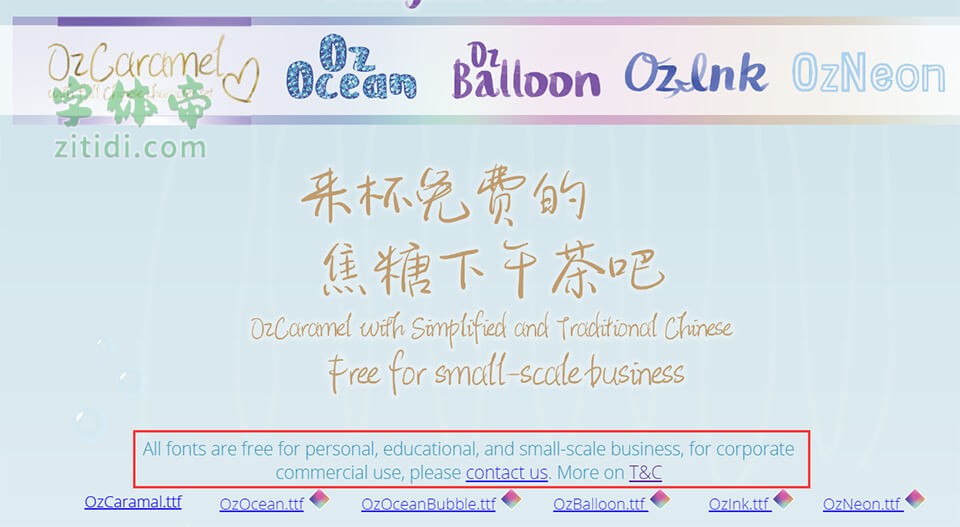
OZ焦糖体是新蒂字体在2020年推出的一款针对个人和小型企业的免费商用字体。OZ焦糖体是一款手写字体,其字形活泼可爱,清秀的字体有着灵动的特质,特别适合小清新,小文艺的设计风格。OZ焦糖体支持超过10000+简体字、繁体字、拉丁字母,可以说是比较齐全了。
“Oz焦糖下午茶”是一款书写很新颖的字体,字体大方,适合各种设计作品使用!欢迎下载!